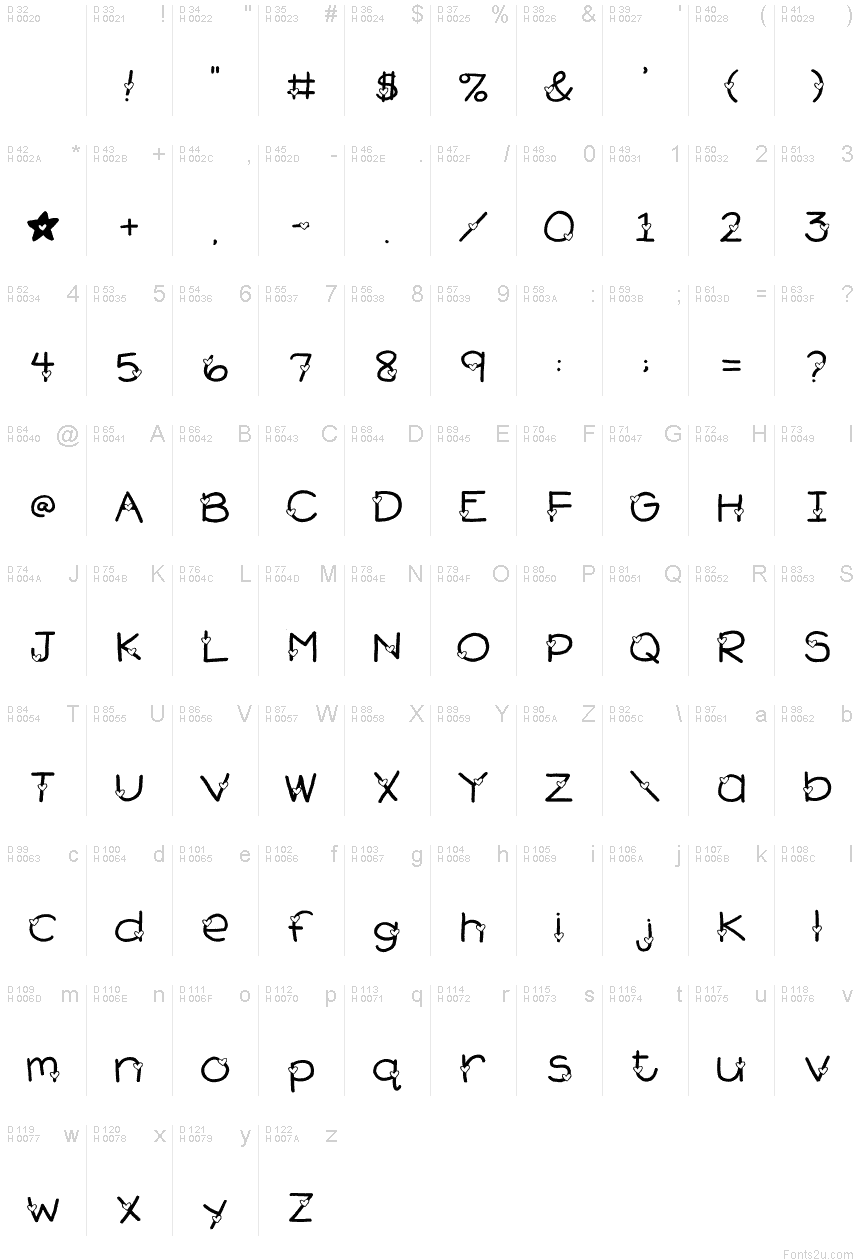
2Peas Heart's Delight autorstwa Melissa Baxter to darmowy, odręcznie rysowany krój display z zaokrąglonymi pociągnięciami i małymi serduszkami wplecionymi w formy liter. Jej nieregularne krzywe i łagodnie zmieniające się proporcje nadają literom swobodny, osobisty charakter. Motyw serca jest częścią konstrukcji, a nie dodaną ozdobą.
Marka papiernicza lub prezentowa mogłaby go użyć do opakowań, zaproszeń i grafik imprezowych o uroczym, domowym charakterze. Litery mogą również posłużyć jako prosty, ilustrowany emblemat.